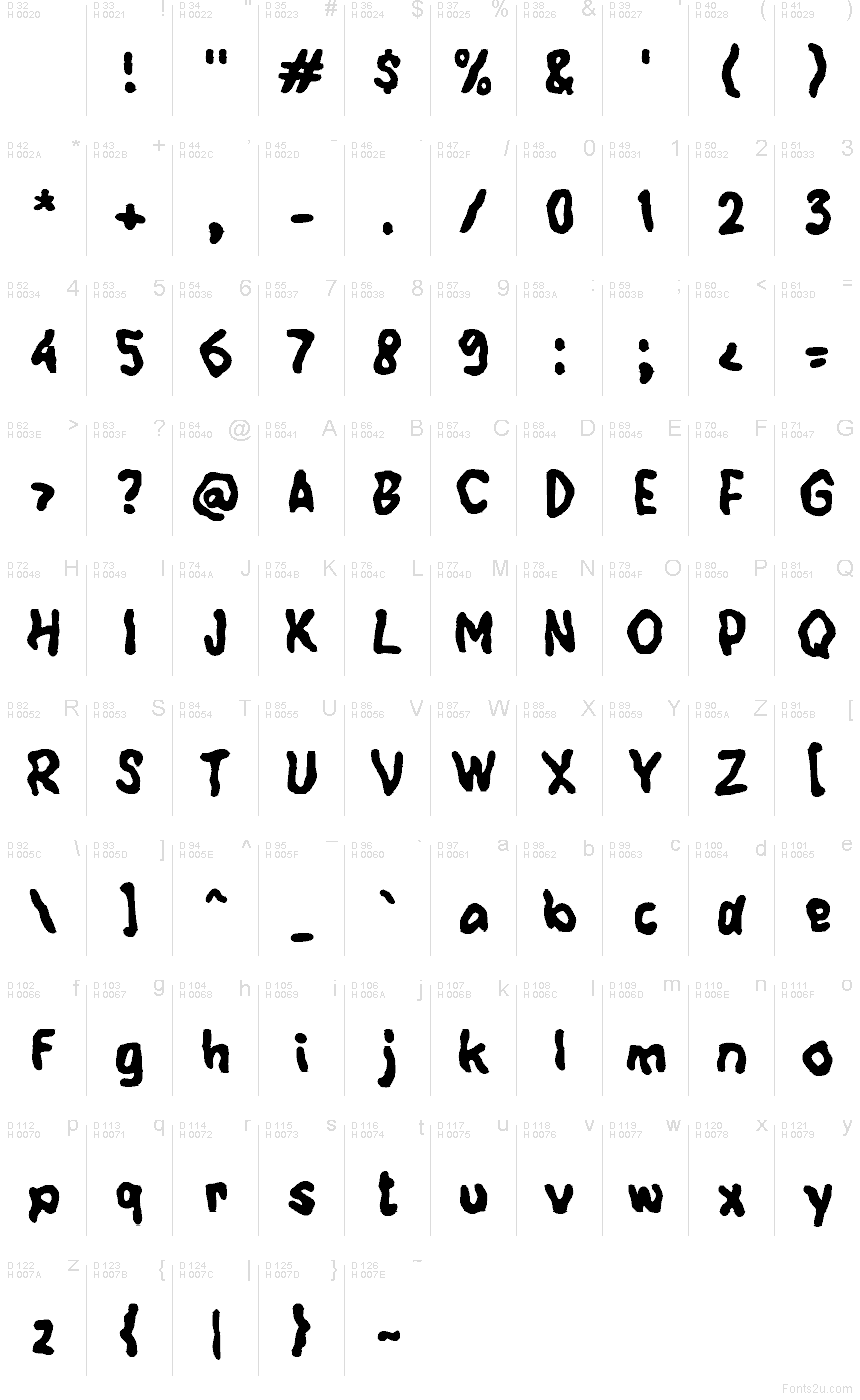
Xabeson od Wep je bezplatné, výrazné titulkové písmo s hravým, až roztopeným vzhľadom, akoby bolo tvarované rukou. Písmená pôsobia plným, mäkkým dojmom, sú mierne nepravidelné, s mohutnými krivkami a kolísavými ťahmi, čo dodáva celému fontu prívetivý a uvoľnený charakter.
Hodí sa na plagáty, obálky zinov, hudobnú grafiku, skejtovú estetiku či balenia v štýle nálepiek, kde je dôležitejšia surová energia než dokonalosť. Keďže ide o bezplatný font, skvele funguje v krátkych nadpisoch, na merch či výraznú grafiku na sociálne siete. Nepravidelné tvary a mohutné siluety dodávajú krátkym slovám živý a prístupný výraz.